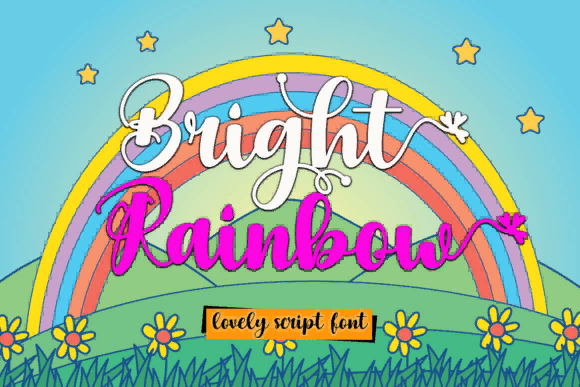
[Creativefabrica] Bright Rainbow Font (2021)
Название: Bright Rainbow Font (2021)
[Creativefabrica] Bright Rainbow Font (2021)
Bright Rainbow - это элегантный, скорописный и веселый рукописный шрифт.
У него красивые и сбалансированные символы, и поэтому он подходит для самых разных дизайнов.